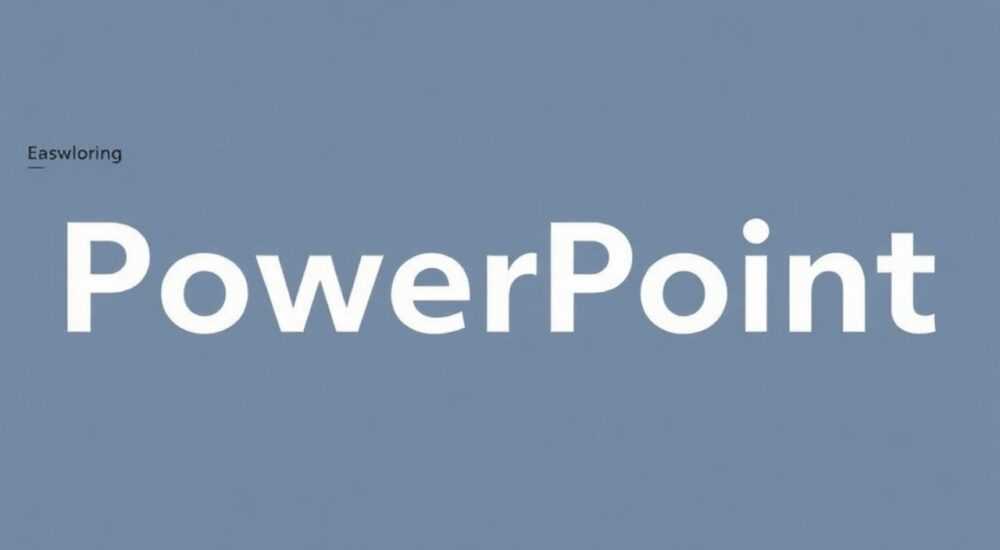
Как добавить свой шрифт в powerpoint
Когда вы работаете с презентациями в PowerPoint, стандартный набор шрифтов может показаться ограниченным. Особенно это касается профессионалов, которым важно поддерживать корпоративный стиль или создавать уникальный дизайн. Представьте ситуацию: вы готовите важную презентацию для клиента, и ваш фирменный шрифт, который используется во всех материалах компании, отсутствует в списке доступных вариантов. Эта проблема особенно актуальна, если вы работаете на разных устройствах или делитесь файлами с коллегами. В материале мы подробно разберем все способы добавления пользовательских шрифтов в PowerPoint, чтобы ваши презентации всегда соответствовали заданным стандартам.
Почему важно использовать собственные шрифты в презентациях
Использование корпоративных или авторских шрифтов в PowerPoint решает несколько ключевых задач. Во-первых, это обеспечивает единство стиля во всех маркетинговых материалах компании. Согласно исследованию Nielsen Norman Group, согласованность визуального оформления повышает узнаваемость бренда на 80%. Во-вторых, правильный выбор шрифта влияет на восприятие информации: san-serif шрифты лучше читаются с экрана, а serif — придают презентации более формальный вид.
- Создание уникального визуального стиля
- Соблюдение брендбука компании
- Улучшение читаемости текста
- Эмоциональное воздействие через типографику
Особенно это важно для компаний, работающих в сфере дизайна, рекламы или IT. Например, цифровое агентство может использовать специфические шрифты-символы для создания интерактивных прототипов прямо в PowerPoint.
Альтернативные методы внедрения шрифтов
Если стандартная установка шрифта невозможна или нежелательна, существуют альтернативные подходы. Первый вариант — использование функции «Внедрить шрифты» при сохранении презентации. Однако этот метод имеет ограничения: не все шрифты поддерживают внедрение, а размер файла значительно увеличивается.
- Временная установка: шрифт устанавливается только на время работы над проектом
- Portable версии: использование переносимых версий PowerPoint с предустановленными шрифтами
- Облачные решения: хранение шрифтов в облаке и автоматическая синхронизация
Например, компания Adobe предлагает решение Typekit, которое позволяет синхронизировать шрифты между устройствами через Creative Cloud. Это особенно полезно для команд, работающих удаленно.
Экспертное мнение: советы от практика
Алексей Петров, ведущий дизайнер презентаций в международной консалтинговой компании «Strategy Partners», делится своим опытом: «За 15 лет работы я столкнулся со множеством ситуаций, когда правильно выбранный шрифт решал судьбу презентации. Помню случай, когда крупный клиент был готов отказаться от сделки из-за ‘несерьезного’ вида документации. После замены стандартного Arial на корпоративный шрифт Montserrat отношение кардинально изменилось.»
По словам эксперта, наиболее частые ошибки при работе с шрифтами:
- Использование слишком мелкого размера текста
- Смешивание более трех различных шрифтов
- Неправильная цветовая контрастность
Ответы на часто задаваемые вопросы
- Необходимо перезапустить программу после установки
- Только при наличии соответствующей лицензии
- Проверяйте условия использования на сайте производителя
- Не все коммерческие шрифты можно внедрять в презентации
- Перейдите в «Файл» → «Сведения» → «Проверить наличие проблем»
- Используйте функцию «Проверить совместимость»
- Откройте файл на другом компьютере для тестирования
Продвинутые техники работы со шрифтами
Современные версии PowerPoint предлагают расширенные возможности работы со шрифтами. Например, функция OpenType Features позволяет использовать специальные глифы, лигатуры и альтернативные символы. Чтобы получить доступ к этим возможностям:
- Выделите текст
- Перейдите в меню «Формат» → «Шрифт»
- Выберите вкладку «Дополнительно»
- Настройте параметры OpenType
Таблица сравнения популярных шрифтов для презентаций:
Шрифт |
Тип |
Лучше использовать для |
Roboto |
Sans-serif |
Хорошая читаемость на экране |
Технические презентации |
Baskerville |
Serif |
Классический внешний вид |